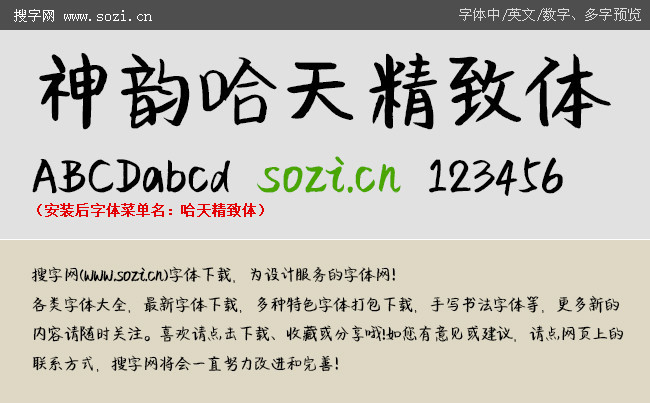
神韻哈天精致體
搜字網(wǎng)給大家提供一款神韻哈天精致體中文字體下載,神韻哈天精致體一款十分美觀的手寫字體,字體流暢大方,整體效果非常出色,適合應(yīng)用于平面海報(bào)設(shè)計(jì)、包裝設(shè)計(jì)等廣告應(yīng)用。(本字體為個(gè)人非商用版,如需要商用請(qǐng)聯(lián)系作者購買版權(quán))